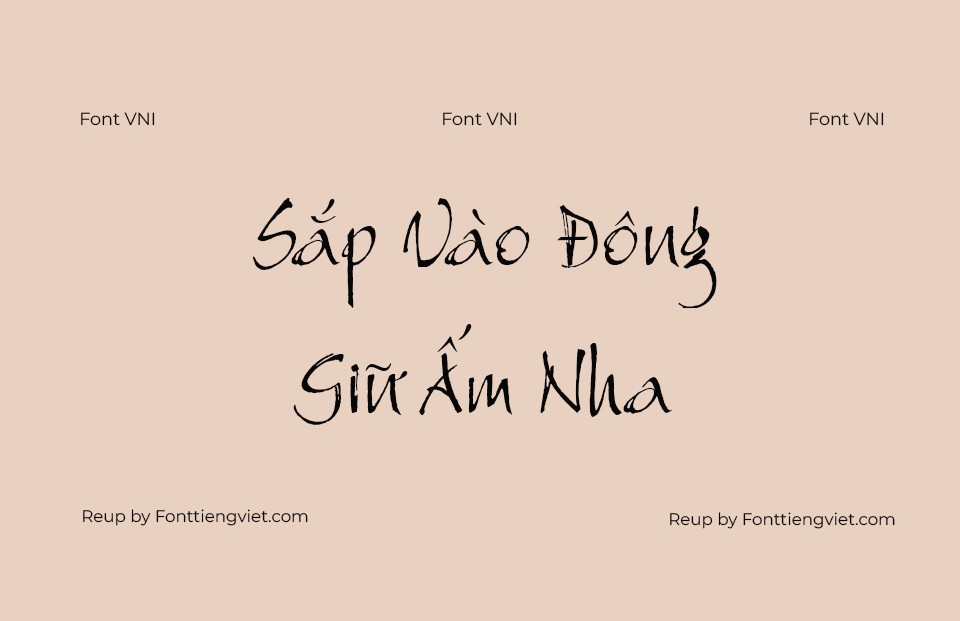
Font Việt hoá VNI 29 BrushMe
Trong thế giới đồ họa hiện đại, việc tìm kiếm một bộ Font Việt hoá VNI 29 BrushMe chất lượng là ưu tiên hàng đầu của nhiều bạn học sinh và giáo viên. Đây là kiểu Font Miễn Phí mang phong cách cọ vẽ đầy cá tính, giúp các bài thuyết trình hay báo tường trở nên sinh động hơn bao giờ hết. Với những nét bút phóng khoáng và mạnh mẽ, bộ phông chữ này không chỉ giữ được cái hồn của nghệ thuật thư pháp hiện đại mà còn đảm bảo tính thẩm mỹ cao cho mọi bản thiết kế tiếng Việt.
Đặc điểm nổi bật của Font Việt hoá VNI 29 BrushMe
Phong cách thiết kế sáng tạo
Bộ Font Việt hoá VNI 29 BrushMe nổi tiếng với những đường nét tự nhiên, mô phỏng chân thực vết mực từ đầu cọ vẽ. Điều này tạo nên cảm giác gần gũi, thủ công nhưng vẫn vô cùng chuyên nghiệp. Các bạn có thể sử dụng nó để làm nổi bật tiêu đề bài học hoặc trang trí bìa sách vở. Sự kết hợp giữa nét thanh và nét đậm giúp văn bản có chiều sâu, thu hút thị giác ngay từ cái nhìn đầu tiên.
Khả năng tương thích tốt
Dù là một font chữ nghệ thuật, nhưng phiên bản Việt hóa này đã được tối ưu hóa hoàn toàn để người dùng không gặp lỗi khi gõ các dấu tiếng Việt phức tạp. Nó hoạt động mượt mà trên nhiều phần mềm văn phòng và đồ họa phổ biến hiện nay. Điều này giúp tiết kiệm thời gian chỉnh sửa và đảm bảo tính thống nhất cho toàn bộ tài liệu học tập.
Cách ứng dụng Font Việt hoá VNI 29 BrushMe hiệu quả
Để đạt hiệu quả cao nhất, bạn nên sử dụng bộ chữ này cho các đoạn văn ngắn hoặc tiêu đề lớn thay vì các khối văn bản dài. Hãy thử kết hợp thêm các màu sắc rực rỡ để tôn vinh vẻ đẹp của nét cọ. Hy vọng bộ Font Miễn Phí, Font Việt Hóa, Font Việt hoá VNI 29 BrushMe này sẽ là công cụ đắc lực giúp bạn sáng tạo ra những sản phẩm tuyệt vời nhất trong môi trường học đường.